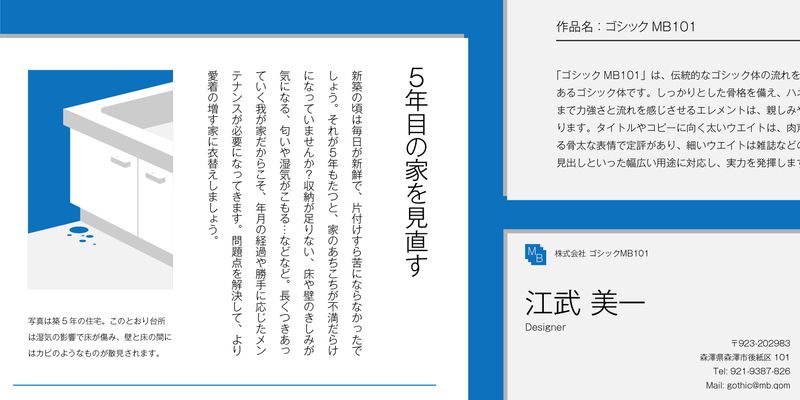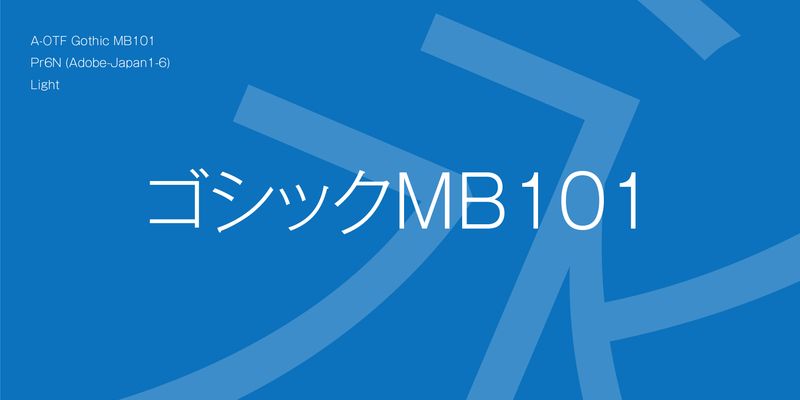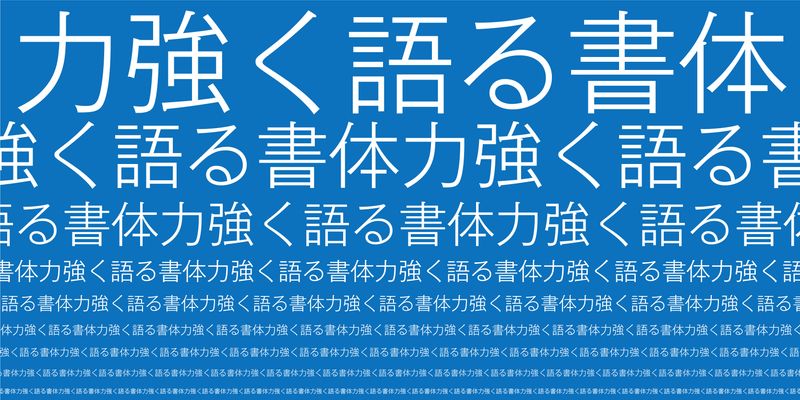
Véritable bête de somme, le Gothic MB101 est une police sans empattement majestueuse, dotée des caractéristiques d’une police sans empattement traditionnel. Sa structure et ses éléments solides donnent à cette police une impression de force et de fluidité, jusqu’aux terminaisons des traits hane (crochet) et harai (balayage). Les graisses lourdes, idéales pour les titres et la publicité, sont connues pour leur solidité qui rappelle la voix humaine, tandis que les graisses légères peuvent être utilisées pour une variété d’applications allant du corps du texte aux titres de taille moyenne dans les magazines.